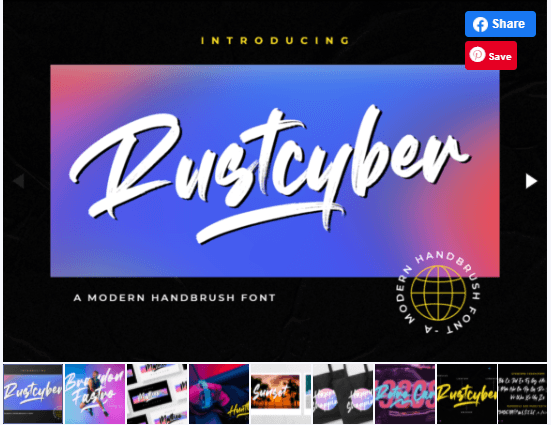
Rustcyber Font
Rustcyber - это классный рукописный шрифт с кисточкой. Добавьте этот жирный шрифт к своим любимым логотипам, одежде, этикеткам и фирменным знакам. Вам понравятся результаты!